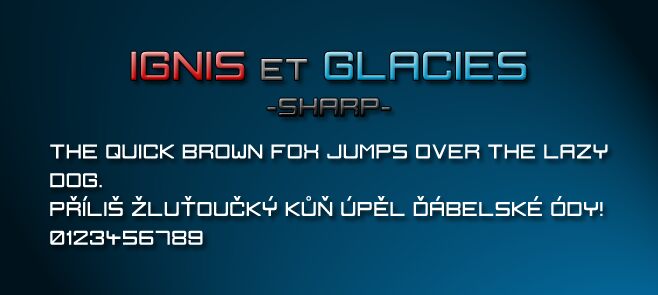
Ignis et Glacies Sharp Bold autorstwa Zdenka Gromnicy to darmowy techniczny krój pisma typu display, który uderza niczym neon w ciemności. Ciężkie, kanciaste formy i ostre jak brzytwa skosy nadają każdemu słowu mocny, inżynieryjny charakter, a ciasne światła sprawiają, że całość sprawia wrażenie zwartej i pełnej napięcia. Font wydaje się jednocześnie mechaniczny i elegancki, przypominając napisy wyryte w szczotkowanym metalu lub interfejsy kokpitów science-fiction.
Dzięki Ignis et Glacies Sharp Bold Twoje nagłówki natychmiast przenoszą się w przyszłość – to świetny wybór do logotypów gier, plakatów sci-fi, brandingu e-sportowego, grafik na konferencje technologiczne, okładek albumów i wyrazistych miniatur na YouTube. Ten darmowy font świetnie sprawdza się w dużych rozmiarach, gdzie jego masywna geometria naprawdę się wyróżnia. Dobrze komponuje się z prostym bezszeryfowym krojem geometrycznym lub lekkim groteskiem w tekstach towarzyszących, co pozwala zachować czystość i czytelność układu.